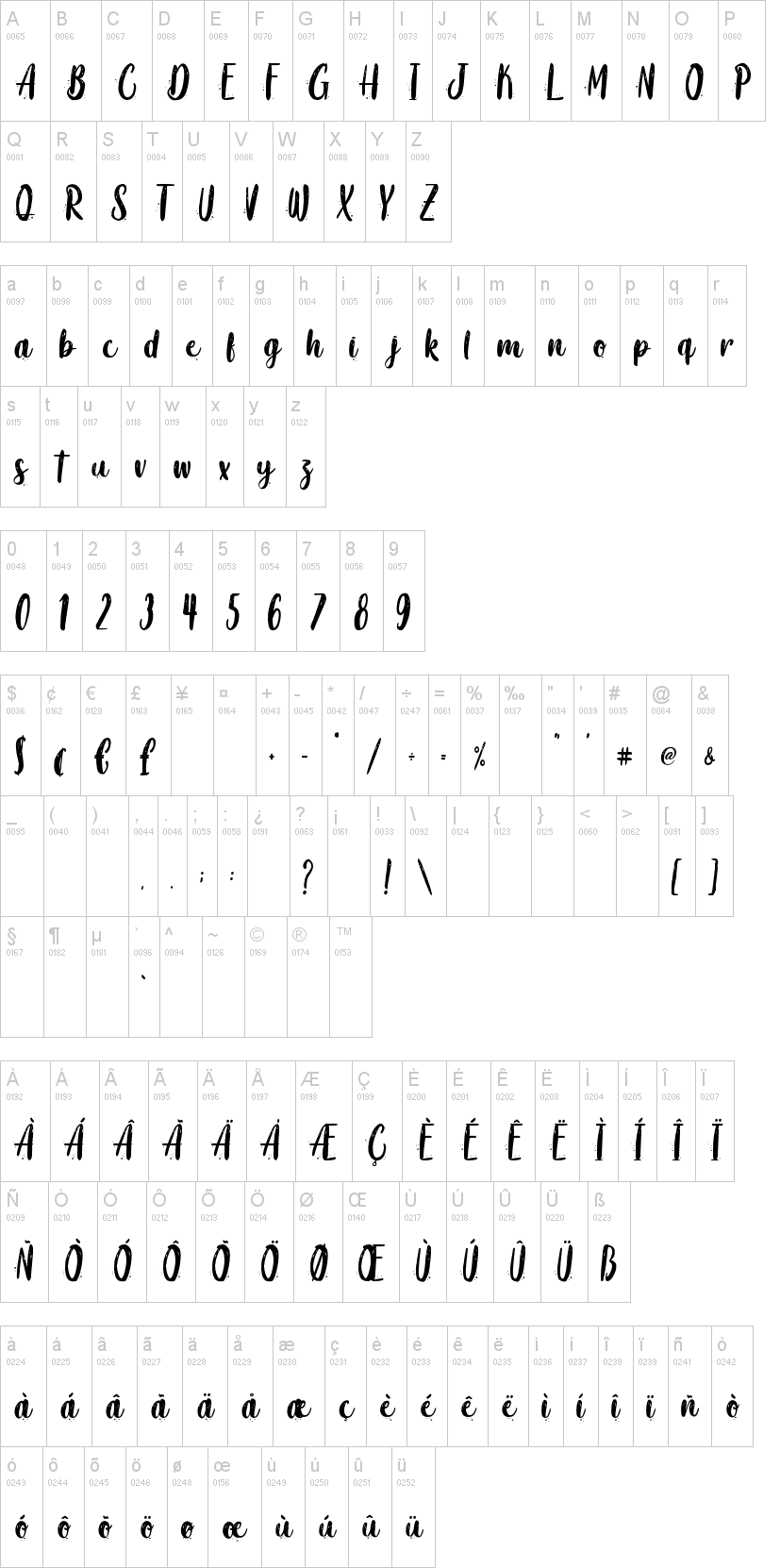
Coaster Quake 是一款具有粗犷,古老的字体,具有极具特色的抖动效果,可以提供极大的视觉冲击力。它的字体特点是让字母看起来像是在颤抖,从而给人一种摇滚的感觉。它适合用于海报,网页,商标,T恤,标志,标题等。内容介绍
Coaster Quake是一款非常不错的手写艺术字体,具有很好的视觉感,适合于文化类的宣传设计、商业类品牌的广告和产品包装设计以及个性化文字排版等较多场景。